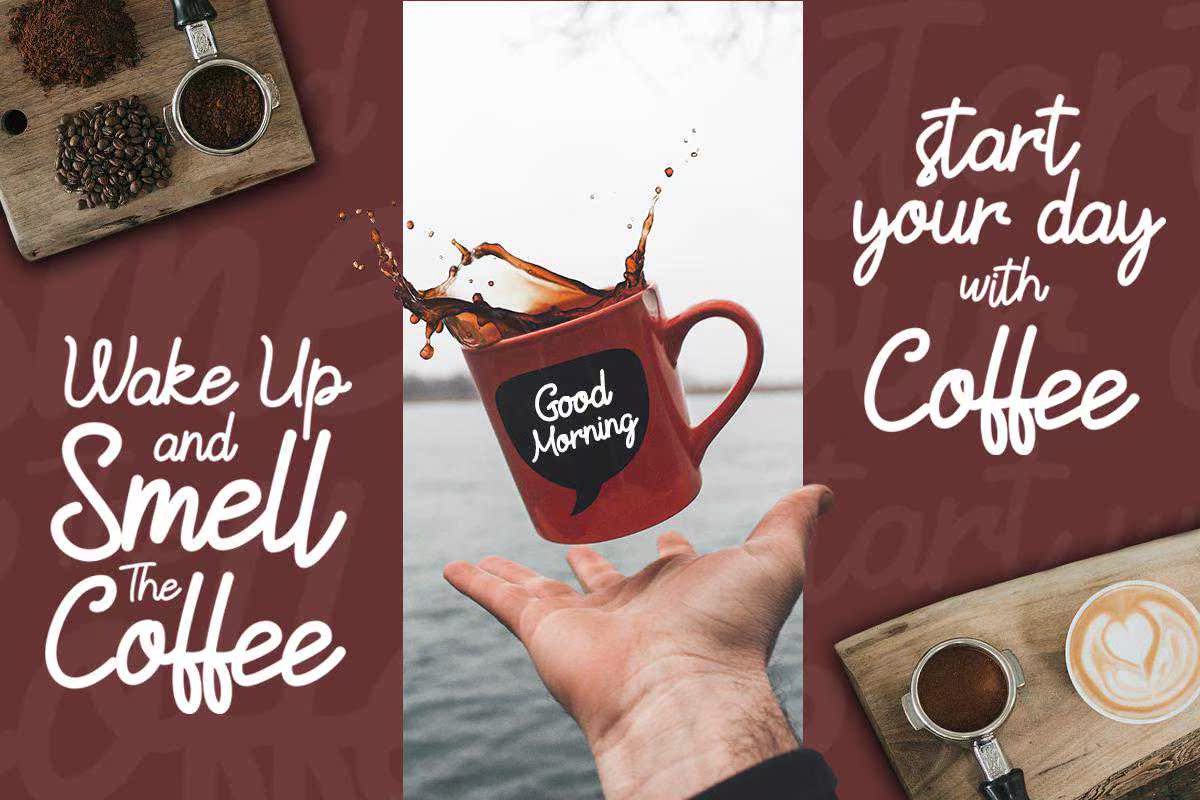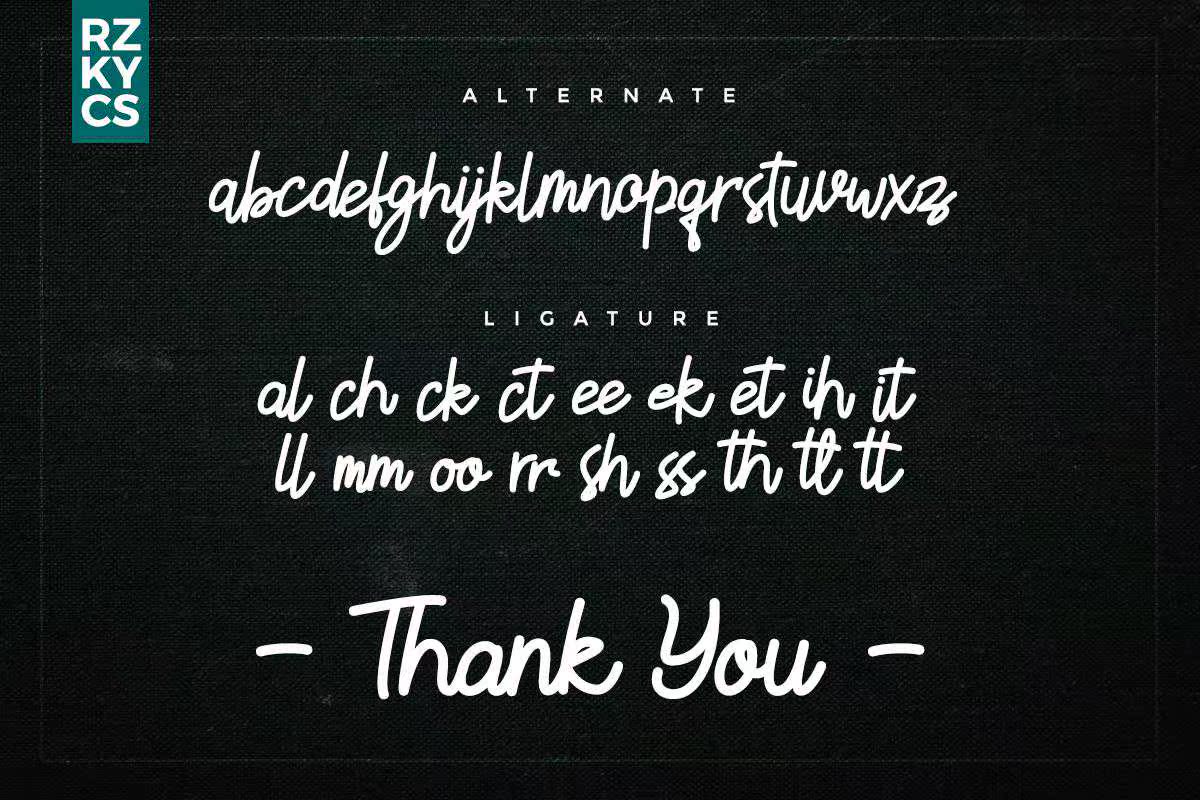
SlaitMonoline是现代字体。Font With Love适用于需要字体作为标题、标识、特价、旅游促销、时尚活动、服装、邀请、品牌、包装、广告的用户。此字体包括大写、小写、标点符号、数字、连字和替换。SlaitMonoline是现代字体。Font With Love适用于需要字体作为标题的用户,徽标、specialevent、TravelPromoto、fashionevent、服装、邀请函、品牌、包装、广告等。此字体包括大写、小写、标点符号、数字、连字和其他字体。